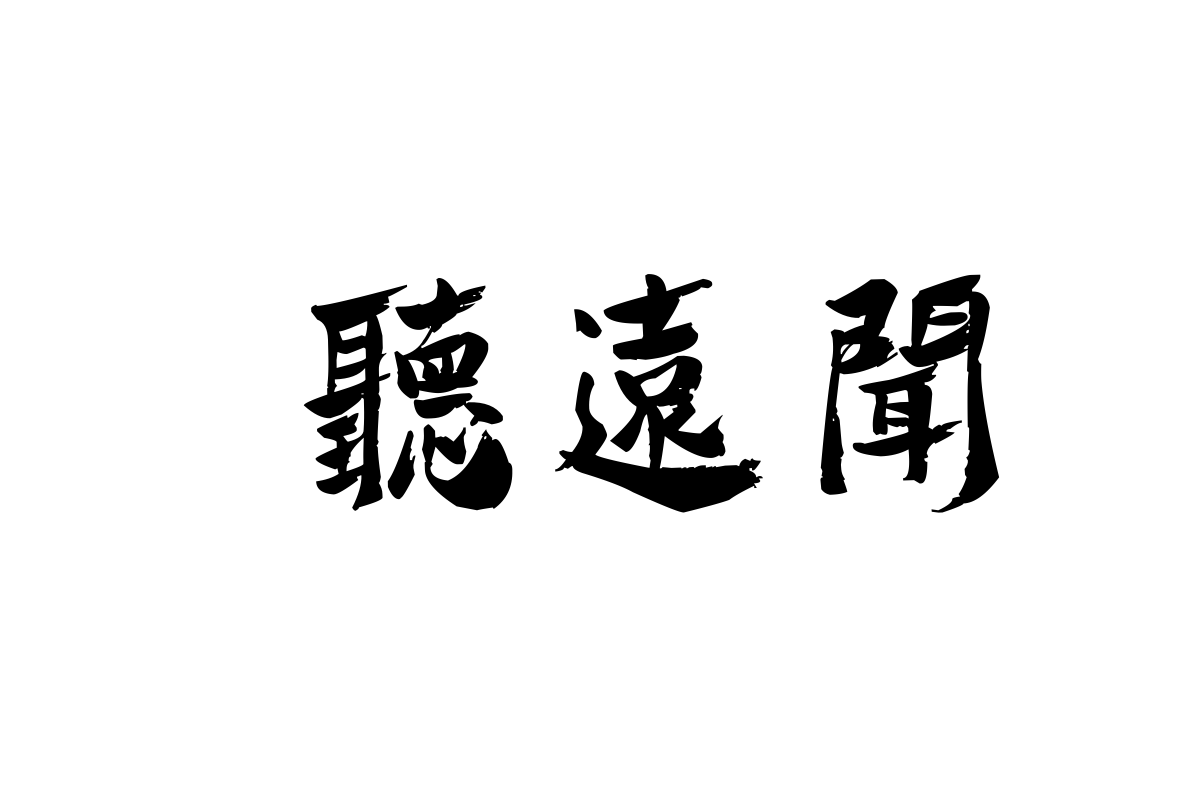
汉标高清馆诗繁字体是一款专为中文书写设计的字体,具有以下特点:
1. 字形美观:汉标高清馆诗繁字体的字形结构优美,笔画流畅,整体给人一种优雅、大方的感觉。
2. 易读性强:该字体在设计时充分考虑了易读性,使得阅读起来更加顺畅,不易产生视觉疲劳。
3. 适用范围广:汉标高清馆诗繁字体适用于各种场合,如正式文件、商业广告、书籍封面等,能够满足不同用户的需求。